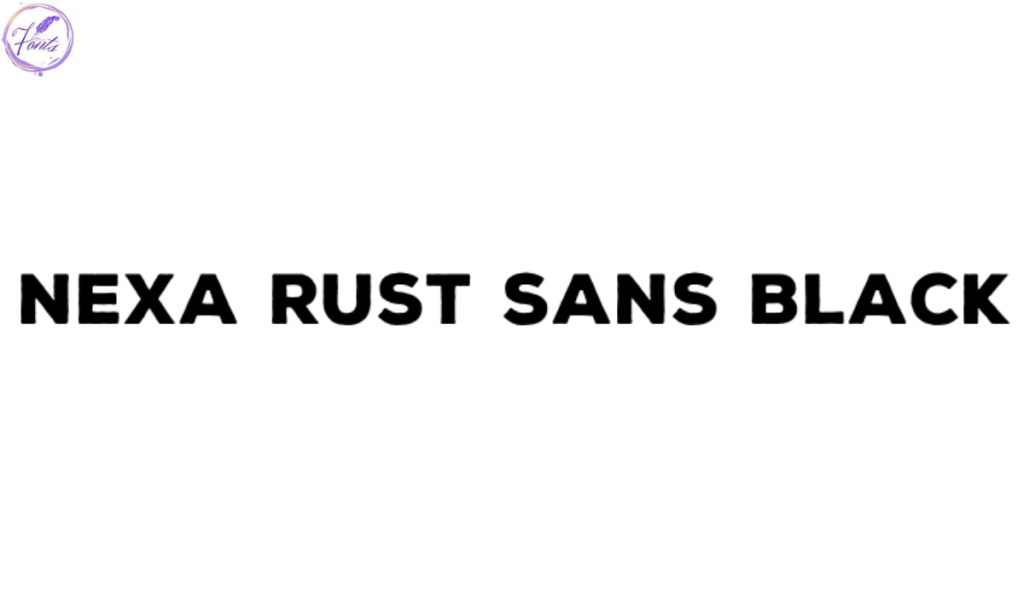
Nexa Rust Sans Black font việt hóa
Tác giả: Dinamo Type Foundry
Ngày phát hành: 2022
Ngôn ngữ: Tiếng Việt, Tiếng Anh, và nhiều ngôn ngữ khác
Bộ Font: Nexa Rust
Phân loại: Cá tính, độc đáo
Kiểu chữ: Kiểu chữ không chân
Độ dày: Nexa Rust Sans Black
Nexa rust sans black font là một font chữ nổi bật với phong cách mạnh mẽ và cá tính. Được thiết kế và vào năm 2022 bởi Dinamo Type Foundry, font này nhanh chóng thu hút sự chú ý nhờ vào thiết kế độc đáo và sự phù hợp với nhiều loại dự án khác nhau. Với các đường nét rõ ràng và sắc nét, nexa rust sans black font không chỉ dễ đọc mà còn mang lại cảm giác hiện đại và năng động. Khả năng tương thích tốt với tiếng Việt là một điểm cộng lớn, giúp bạn dễ dàng tạo ra những thiết kế ấn tượng và chuyên nghiệp.
Đánh giá nexa rust sans black font
Nexa rust sans black font nhận được nhiều đánh giá tích cực từ cộng đồng thiết kế. Font này nổi bật với sự đa dụng, có thể sử dụng trong nhiều loại dự án từ thiết kế logo, tiêu đề, đến các banner quảng cáo. Các nhà thiết kế đánh giá cao độ sắc nét và tính nhất quán của các ký tự, cùng với khả năng truyền tải thông điệp mạnh mẽ. Đặc biệt, nexa rust sans black font rất phù hợp cho những dự án cần sự nổi bật và ấn tượng. Đây là một lựa chọn tuyệt vời cho bất kỳ ai đang tìm kiếm một font chữ mạnh mẽ và đậm chất cá tính.